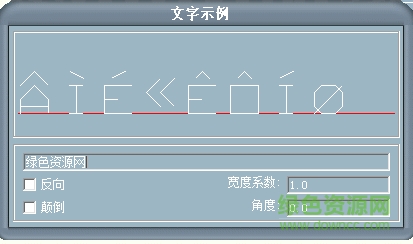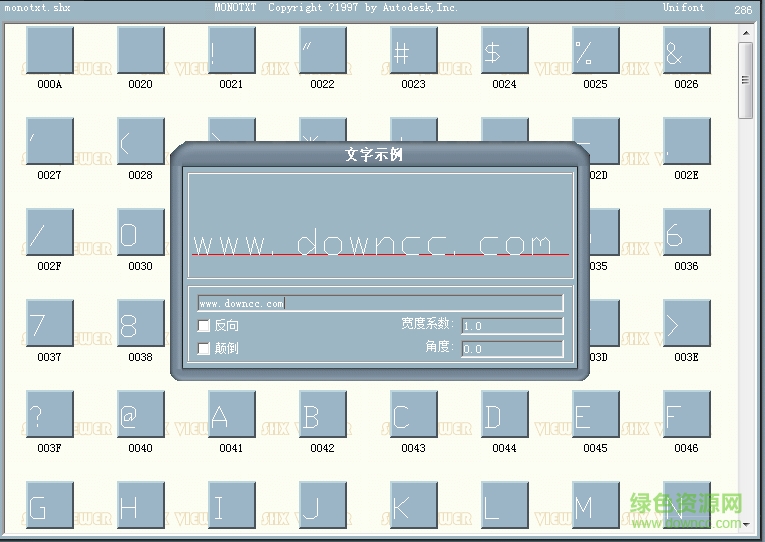
monotxt.shx
monotxt.shx字體是一款等寬的autocad文字字體,包含各種特殊的數(shù)字符號(hào)和文字符號(hào),該字體可以幫助用戶更好地查看CAD圖紙,安裝使用步驟附以下,有需要者快來(lái)下載吧!
【txt】標(biāo)準(zhǔn)的 AutoCAD 文字字體。 這種字體可以通過(guò)很少的矢量來(lái)描述,它是一種簡(jiǎn)單的字體,因此繪制起來(lái)速度很快,txt字體文件為txt.shx。
【monotxt】 等寬的 txt 字體。 在這種字體中,除了分配給每個(gè)字符的空間大小相同(等寬)以外,其他所有的特征都與txt字體相同。因此,這種字體尤其適合于書寫明細(xì)表或在表格中需要垂直書寫文字的場(chǎng)合。